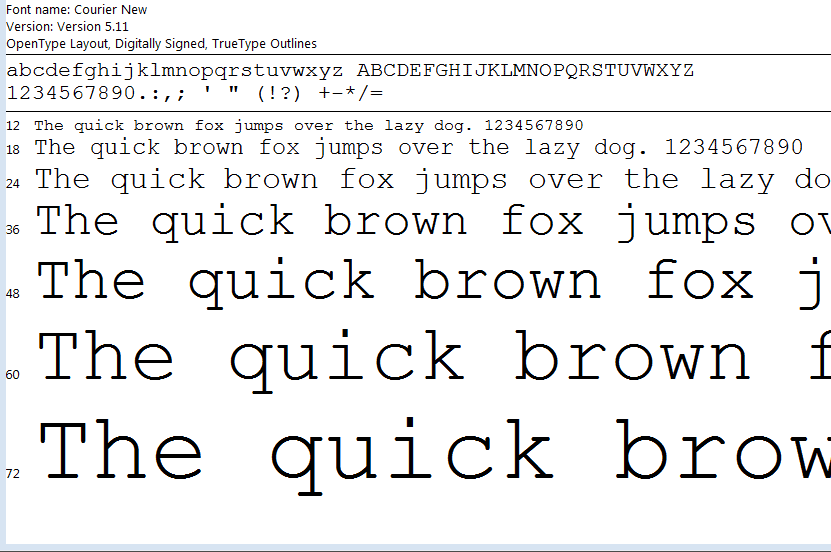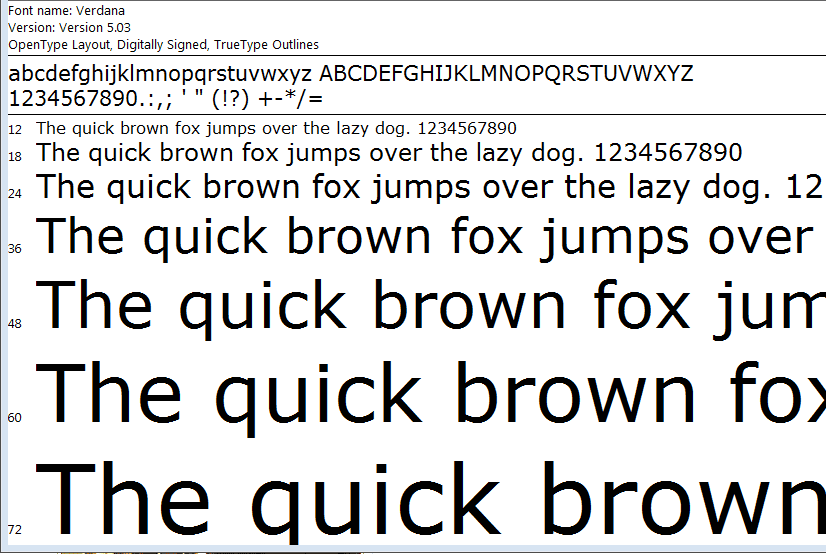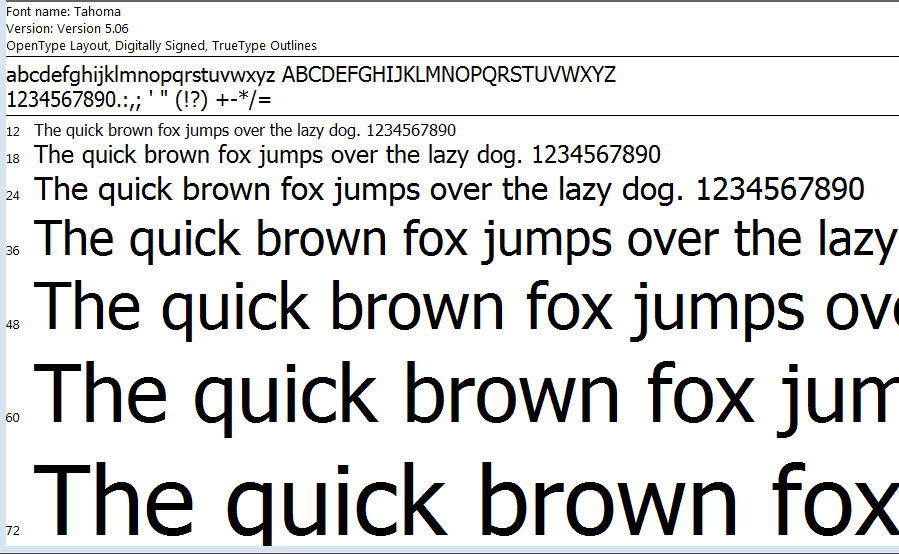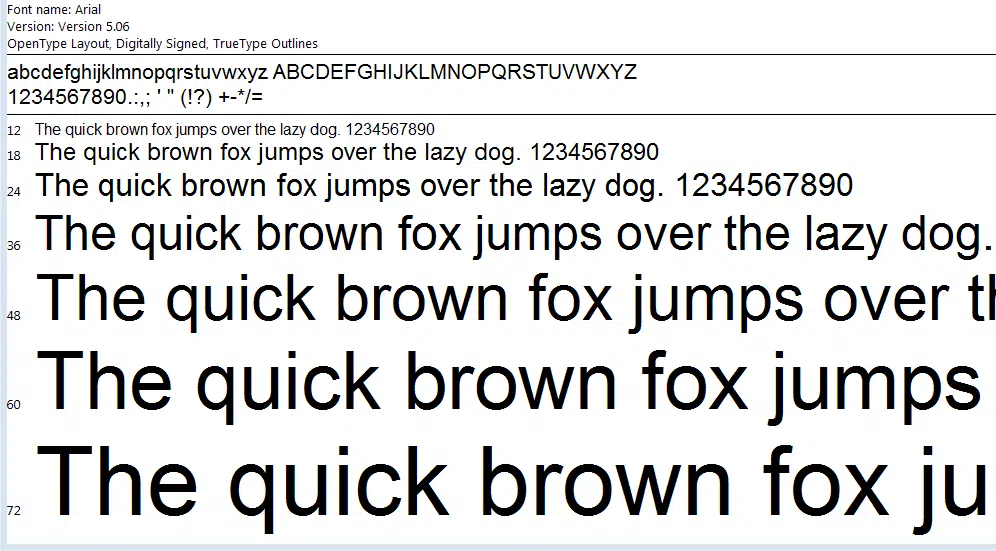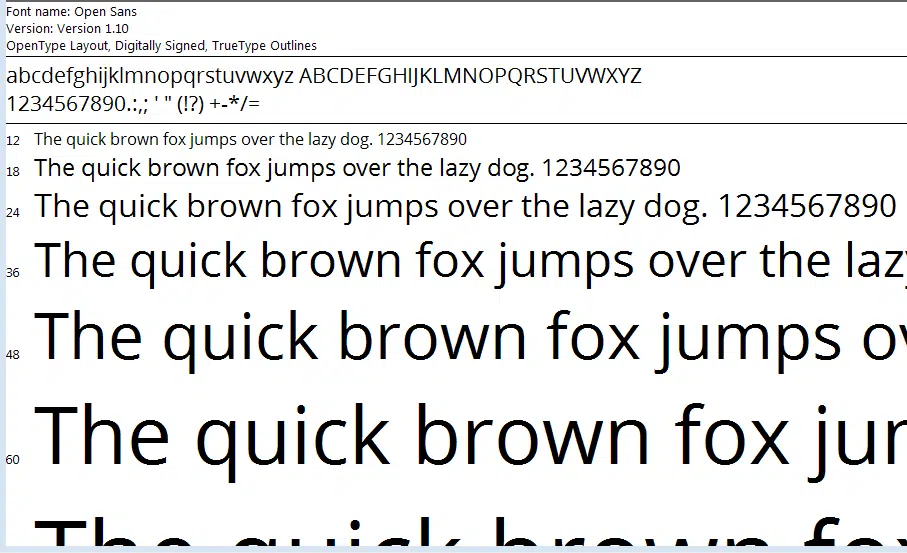
Top 10 font chữ thiết kế website đẹp mà bạn nên dùng
Font chữ thiết kế website không chỉ là phần “trang trí” cho giao diện. Font chữ ảnh hưởng trực tiếp đến cách người dùng đọc nội dung, cảm nhận thương hiệu và quyết định có tiếp tục ở lại website hay không. Một website có bố cục đẹp nhưng font khó đọc vẫn có thể khiến khách hàng rời trang nhanh.
Khi chọn font cho website, bạn cần nhìn xa hơn yếu tố thẩm mỹ. Font phải dễ đọc, hỗ trợ tiếng Việt tốt, phù hợp với ngành nghề, hiển thị ổn định trên nhiều thiết bị và không làm website tải chậm. Bài viết này sẽ giúp bạn hiểu cách chọn font chữ thiết kế website chuyên nghiệp, dễ ứng dụng và phù hợp với mục tiêu chuyển đổi.
Font chữ thiết kế website là gì?
Font chữ thiết kế website là kiểu chữ được sử dụng để hiển thị nội dung trên website. Font có thể xuất hiện ở tiêu đề, đoạn văn, menu, nút kêu gọi hành động, biểu mẫu, banner, bảng giá và nhiều thành phần khác trong giao diện.
Một font chữ phù hợp giúp website rõ ràng, dễ đọc và có tính nhận diện tốt hơn. Ngược lại, một font không phù hợp có thể khiến giao diện thiếu chuyên nghiệp, khó nhìn hoặc không truyền tải đúng tinh thần thương hiệu.
Typography Trong Web Design: Tại Sao Lại Quan Trọng Đến Vậy?
Typography không chỉ là việc chọn một kiểu chữ cho đẹp. Trong thiết kế website hiện đại, Typography chiếm đến 90% diện tích thiết kế và đóng vai trò như “người dẫn đường” định hướng toàn bộ trải nghiệm người dùng.
Ảnh hưởng đến Trải nghiệm người dùng (UX) và Tính dễ đọc
Một font chữ tốt giống như một giọng nói rõ ràng, truyền cảm. Nó giúp người dùng tiếp thu thông tin một cách mượt mà, không bị mỏi mắt dù đọc trên màn hình điện thoại bé xíu hay màn hình máy tính lớn. Nếu font chữ quá mỏng, khoảng cách chữ quá hẹp, người dùng sẽ nhanh chóng cảm thấy chán nản và rời bỏ website trước khi kịp đọc đến nút “Mua hàng”.
Định hình phong cách và Nhận diện thương hiệu (Branding)
Font chữ chính là “tính cách” của thương hiệu. Bạn không thể dùng một font chữ bay bướm, hài hước cho website của một công ty luật; ngược lại, một font chữ quá cứng nhắc sẽ giết chết sự sáng tạo của một agency quảng cáo. Việc đồng nhất Typography giúp khách hàng ghi nhớ và nhận diện thương hiệu của bạn ngay cả khi chưa nhìn thấy logo.
Tác động đến Tốc độ tải trang và Điểm SEO (Core Web Vitals)
Nhiều người bỏ qua yếu tố này, nhưng việc tải quá nhiều font chữ hoặc sử dụng font có dung lượng lớn sẽ trực tiếp kéo tụt điểm SEO của website.
- Font chữ chưa được tối ưu sẽ làm tăng thời gian LCP (Largest Contentful Paint) – thời gian hiển thị nội dung chính.
- Hiện tượng “chớp font” (FOUT/FOIT) khi tải trang sẽ làm bố cục bị giật lag, gây ảnh hưởng nghiêm trọng đến chỉ số CLS (Cumulative Layout Shift) – một trong những yếu tố xếp hạng cực kỳ quan trọng của Google.
Tổng Hợp Các Font Chữ Thiết Kế Website Đẹp và Chuẩn Nhất Hiện Nay
Không phải font nào cũng phù hợp với website. Khi thiết kế giao diện, copywriter và designer cần hiểu các nhóm font cơ bản để chọn đúng theo mục đích sử dụng.
Font chữ thiết kế website Arial
Arial là font chữ thiết kế website được sử dụng phổ biến hiện nay. Arial đảm bảo tiêu chuẩn về một font chữ an toàn.
Font chữ thiết kế website Arial
Font chữ thiết kế website Open Sans
Open Sans là font chữ thiết kế website ấn tượng. Nó hỗ trợ đầy đủ tiếng Việt có dấu, nội dung được trình bày rõ ràng, đẹp mắt.
Font chữ thiết kế Open Sans
Font chữ thiết kế website Helvetica
Font chữ Helvetica là font chữ đặc trưng, được sử dụng cho rất nhiều mục đích khác nhau. Font chữ này được phát triển bởi một nhà thiết kế người Thụy Điển có tên Max Miedinger. Helvetica giúp cho người đọc không gặp khó khăn ngay cả với kích thước nhỏ hay khoảng cách giữa các ký tự quá gần nhau.
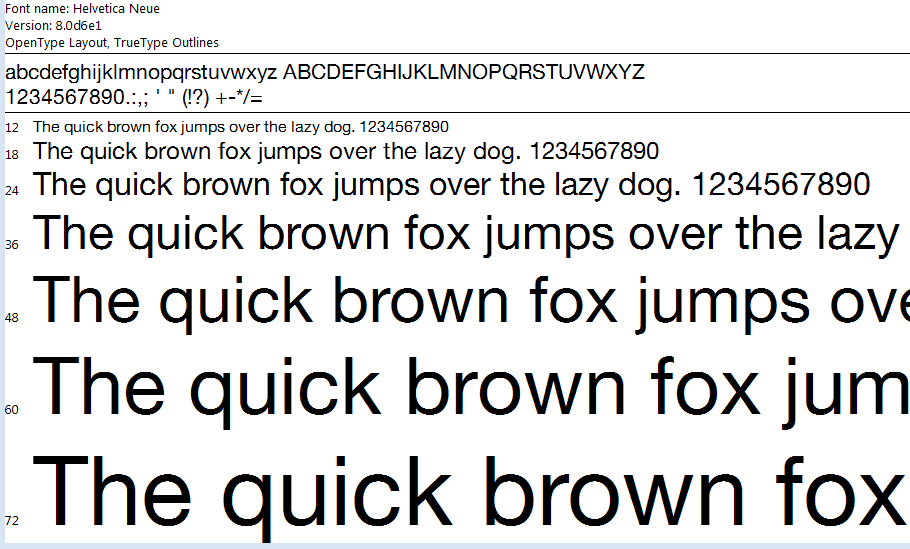
Font chữ thiết kế web Helvetica
Font chữ thiết kế website Bookman
Bookman là font chữ thiết kế web thú vị và tuyệt vời. Font chữ này chủ yếu được dùng để làm tiêu đề bởi vì người đọc có khả năng đọc được dễ dàng ngay cả khi ở kích thước nhỏ.
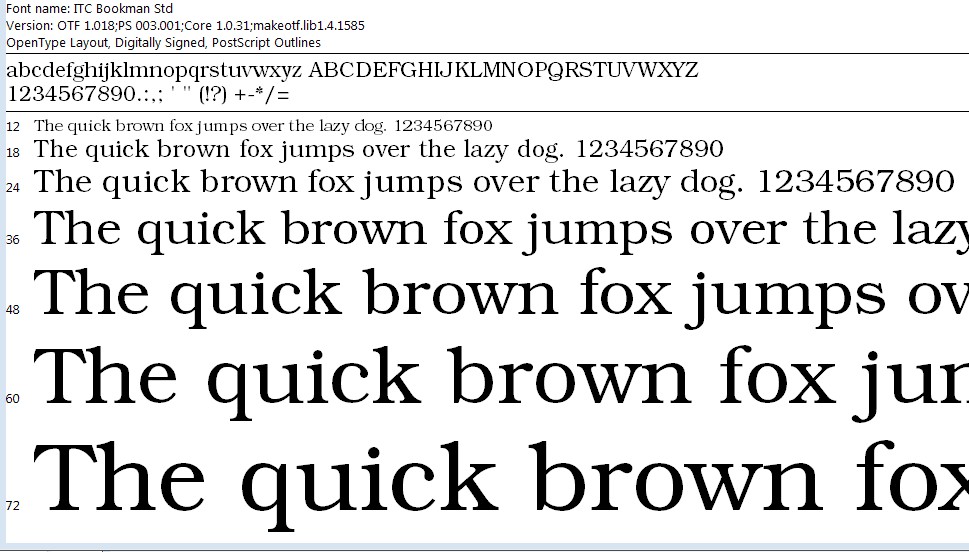
Font chữ thiết kế web Bookman
Font chữ thiết kế website Times New Roman
Times New Roman là font chữ phổ biến, đặc biệt trên các thiết bị chạy hệ điều hành Windows. Hầu hết người học soạn thảo văn bản đều phải làm quen với font chữ Times New Roman. Font chữ này có hỗ trợ Tiếng Việt, phù hợp với những trang báo chí, tài liệu,…
Font chữ thiết kế website Trebuchet MS là font chữ truyền thống, thiết kế bởi Microsoft vào những năm 90. Font chữ này được sử dụng rộng rãi trên các phiên bản XP.
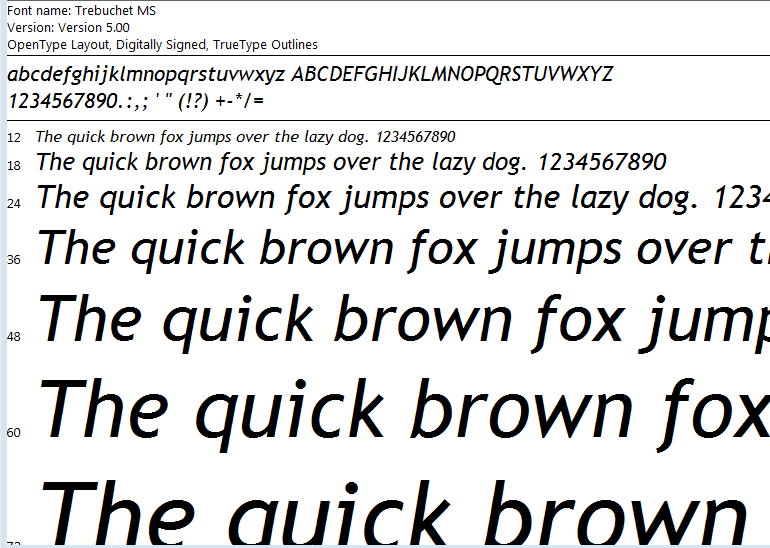
Font chữ thiết kế web Trebuchet MS